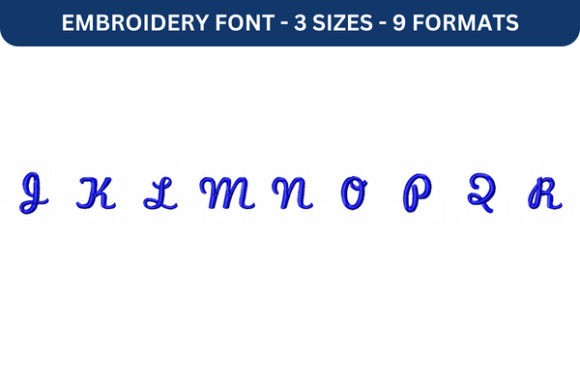
Marketing Script Font Upper J to R
Marketing Script Font Upper J to R와 같은 κ³ ν’ˆμ§ˆ μžμ‚°μ„ μ°Ύκ³  μžˆλ‹€λ©΄ 이 프리미엄 νŒ¨ν‚€μ§€λŠ” 창의적인 ν”„λ‘œμ νŠΈλ₯Ό μœ„ν•œ ν™˜μƒμ μΈ μ„ νƒμž…λ‹ˆλ‹€.
μ •λ°€ν•˜κ²Œ μ œμž‘λœ Marketing Script Font Upper J to RλŠ” κΉ”λ”ν•œ 벑터, λΆ€λ“œλŸ¬μš΄ νƒ€μ΄ν¬κ·Έλž˜ν”Ό 및 μ•ˆμ‹¬ν•  수 μžˆλŠ” μƒμ—…μš© λΌμ΄μ„ μŠ€λ₯Ό μ œκ³΅ν•©λ‹ˆλ‹€.
POD(μ£Όλ¬Έν˜• 인쇄) μ œν’ˆ, κ²°ν˜Όμ‹ μ΄ˆλŒ€μž₯ λ˜λŠ” μ†Œμ…œ λ―Έλ””μ–΄ κ·Έλž˜ν”½μ„ λ§Œλ“€ λ•Œ Marketing Script Font Upper J to RλŠ” 이상적인 μ„ νƒμž…λ‹ˆλ‹€.